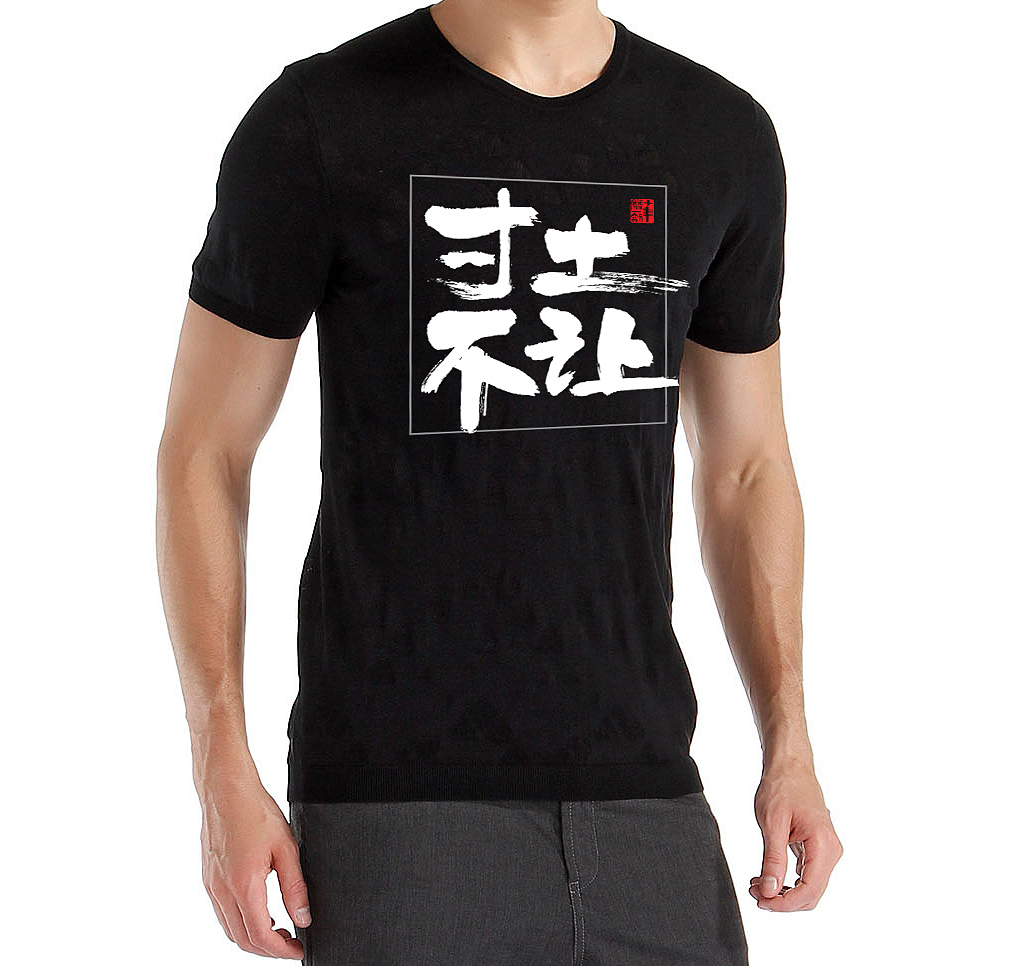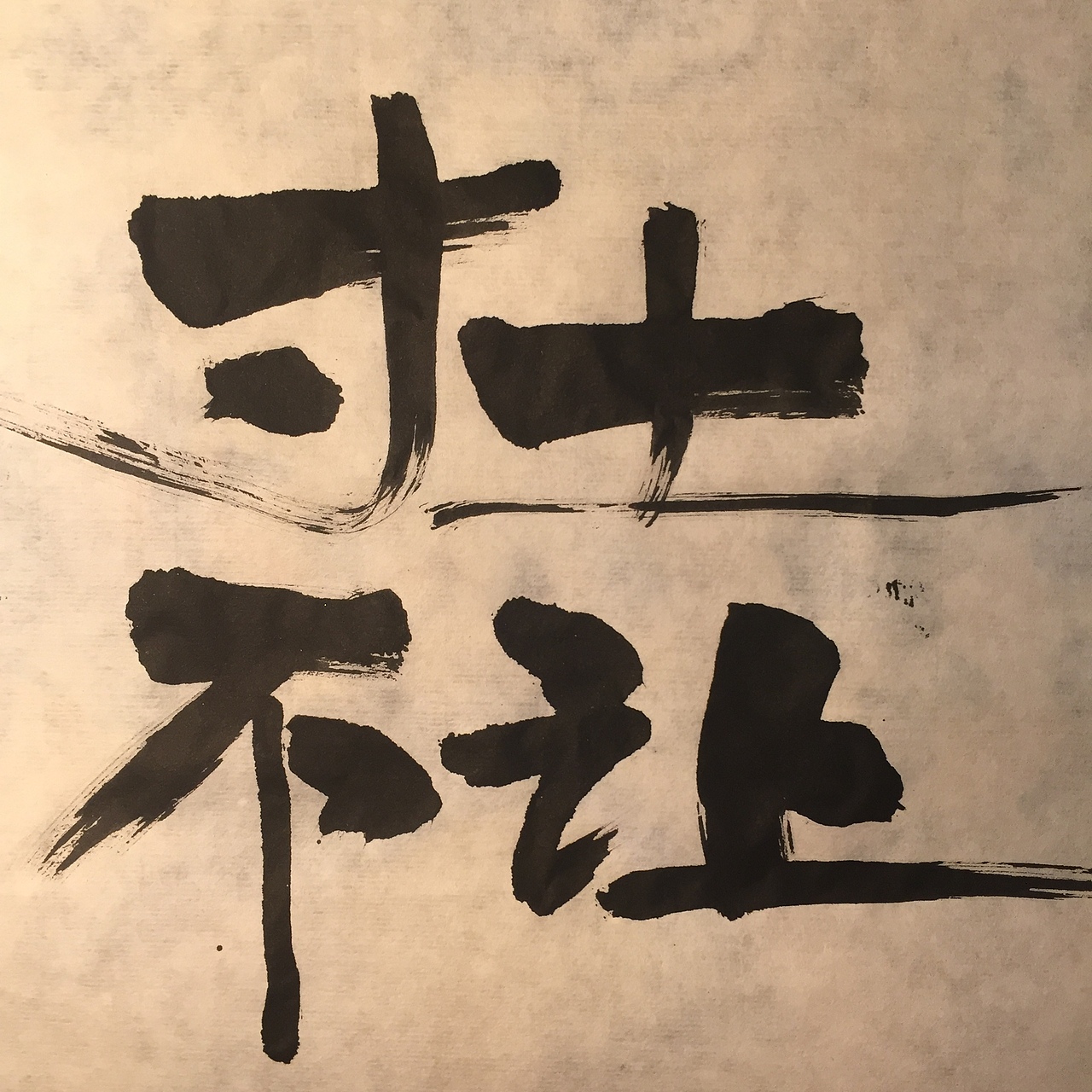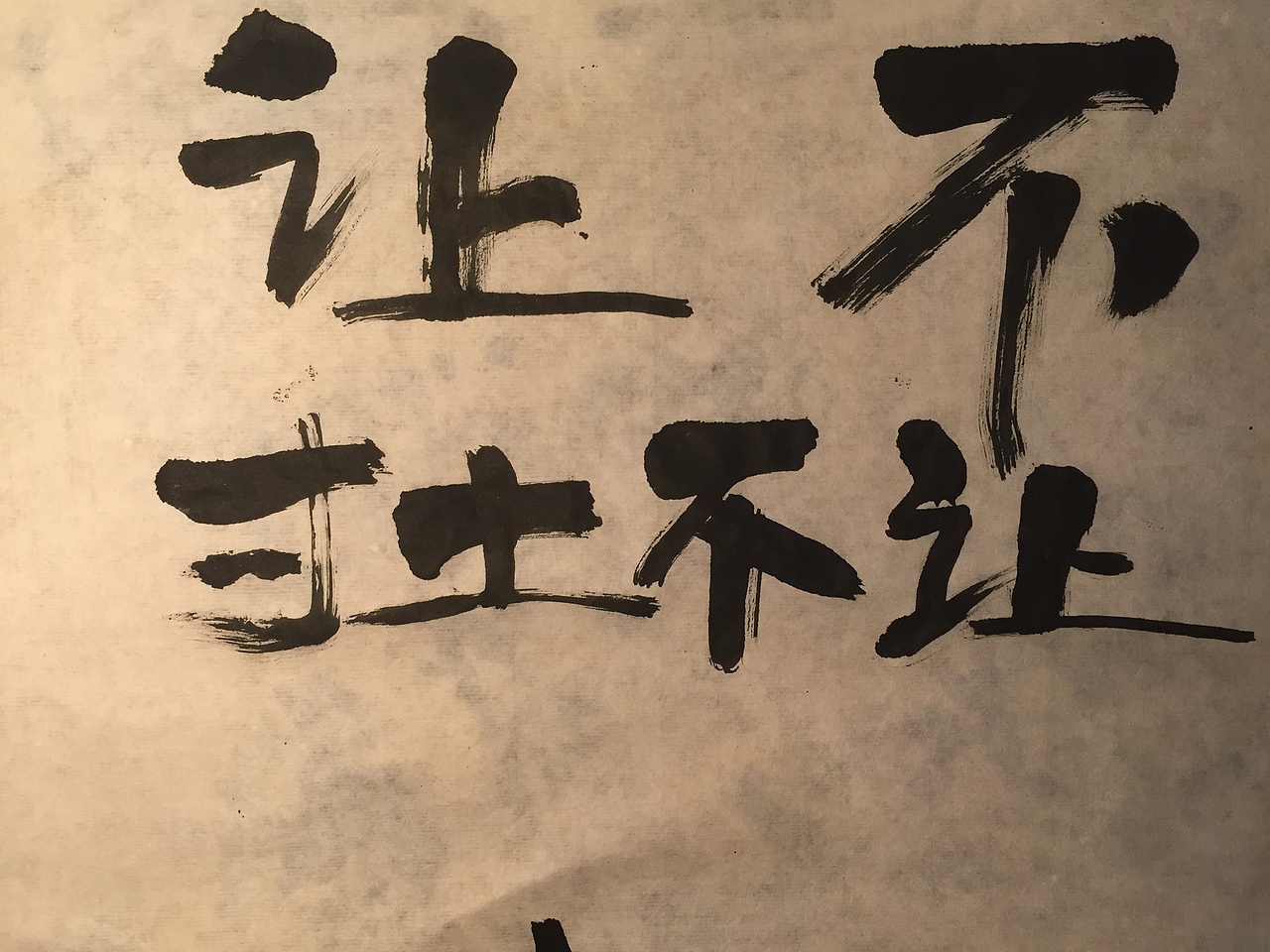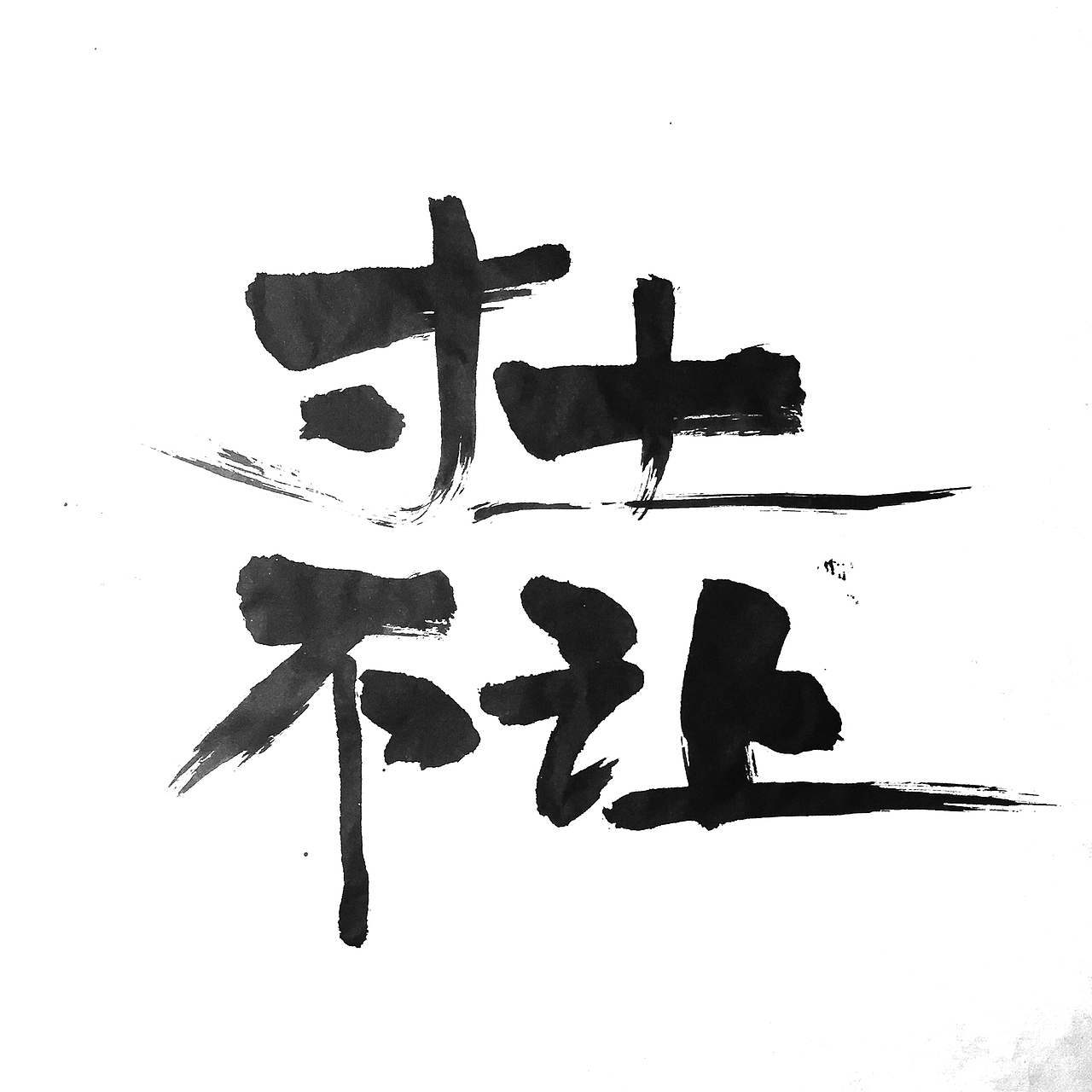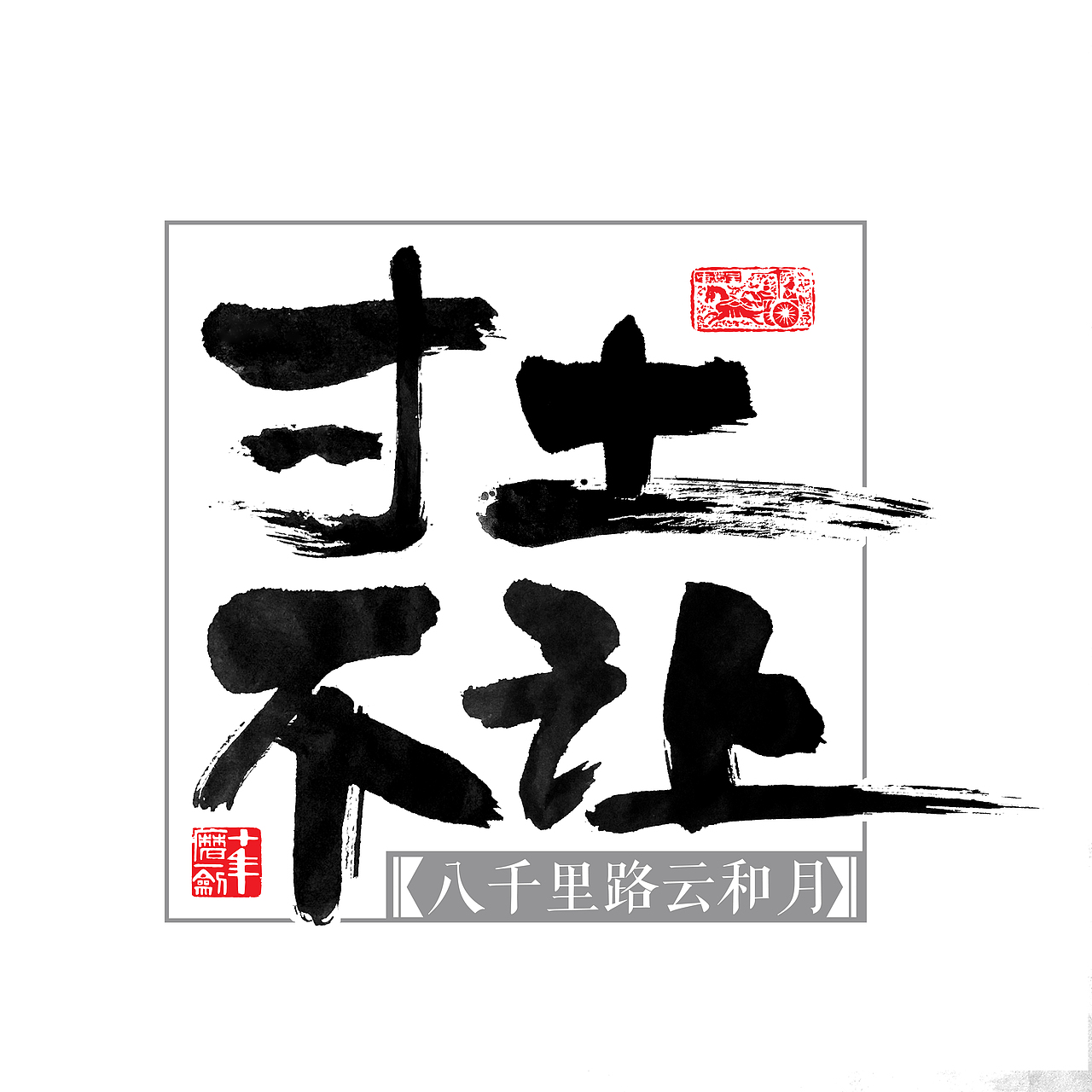
教你制作个性书法工服或情侣装。
最终效果是这样的!
用毛笔写出想要的T恤主题,这次南海仲裁事件所以我写了“寸土不让”几个字。
我在小时候学过几天书法,半途而废。所以写字并不好看,所以多写一些。这个让字还好。
还是让字。多写几个进行比较,最后在ps里面进行比较,看哪个效果更好。
这个图字的飞白比较好,将来效果应该不错。
图片在ps中去色,调整对比度。。同时选取单字,调整字间距和行间距。
把效果不好的字逐一换上其他单个比较好的字,用同一方式进行调整。。
最后补上两枚印章,在T恤上贴图时发现不太规整,加了个灰色的方框。
白色的贴图效果,设计上留白太少,过于满了。
去掉了一枚印章和辅助性文字,效果好了很多。
背面的效果。简单一些也还不错。
用此方法可以制做情侣装、活动工服、工作室的工服等。